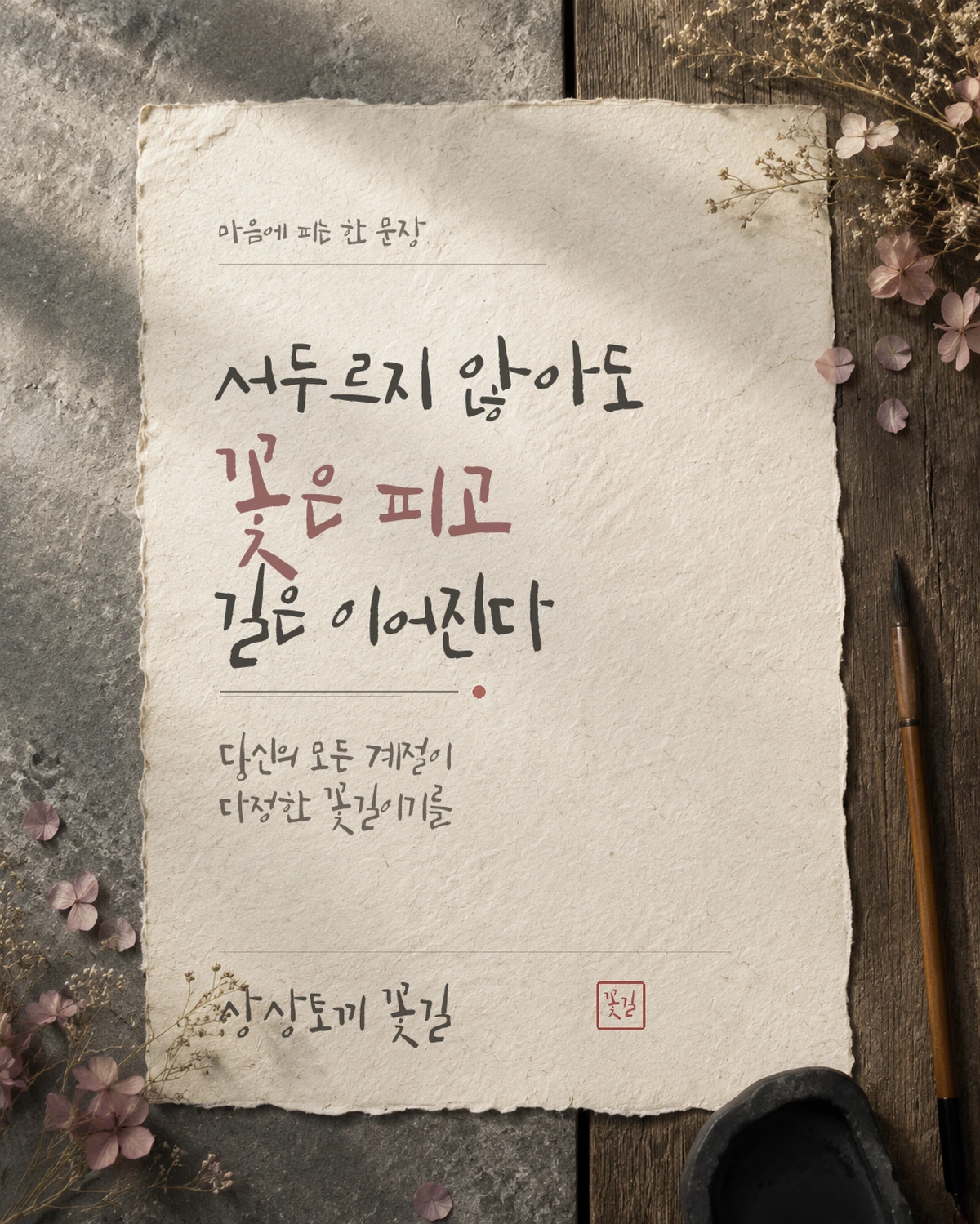
상상토끼 꽃길 — 상상토끼에서 배포하는 무료 폰트입니다. 붓글씨의 자유로운 획과 판화 같은 질감을 살린 개성 있는 캘리그라피 서체
상상토끼의 캘리그래피 서체입니다. 제작사가 남긴 소개에 만들어진 계절까지 적혀 있습니다. 사방 간 데 꽃길 넘실대는 5월에 만들어진 감성 폰트라는 것입니다.
원본은 아이 손글씨가 아니라 붓글씨입니다. 폰트를 만드는 캘리그래퍼로 불리는 상상토끼 용이 작가의 붓글씨를 기초로 만들었다고 밝히고 있습니다. 파일에서 재어 보면 받침 유무에 따라 글자 높이가 달라지는 탈네모틀이고 획에 굵기 변화가 있어, 붓으로 그은 흔적이 남아 있습니다.
굵기는 하나이고 한글은 2,352자입니다. 드문 음절에서는 글자가 빠질 수 있으니 정해진 문구를 조판하는 자리에 쓰세요. 붓글씨 계열이라 제목이나 인용구, 감성 카피처럼 크게 쓰는 자리에 맞고 긴 본문에는 맞지 않습니다. 개인과 기업 모두 상업적으로 쓸 수 있고 재배포도 되지만 파일 수정과 재판매는 금지됩니다.